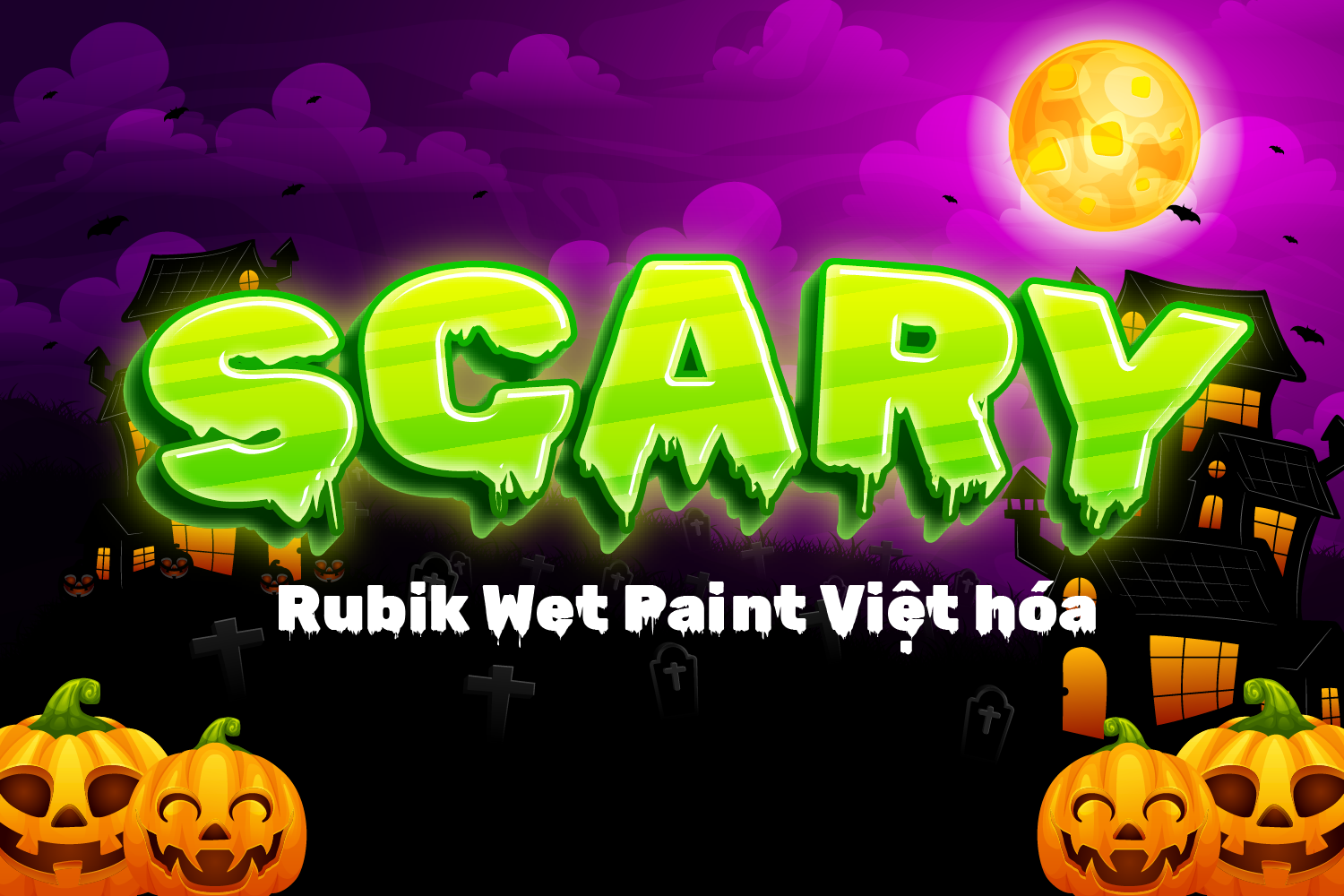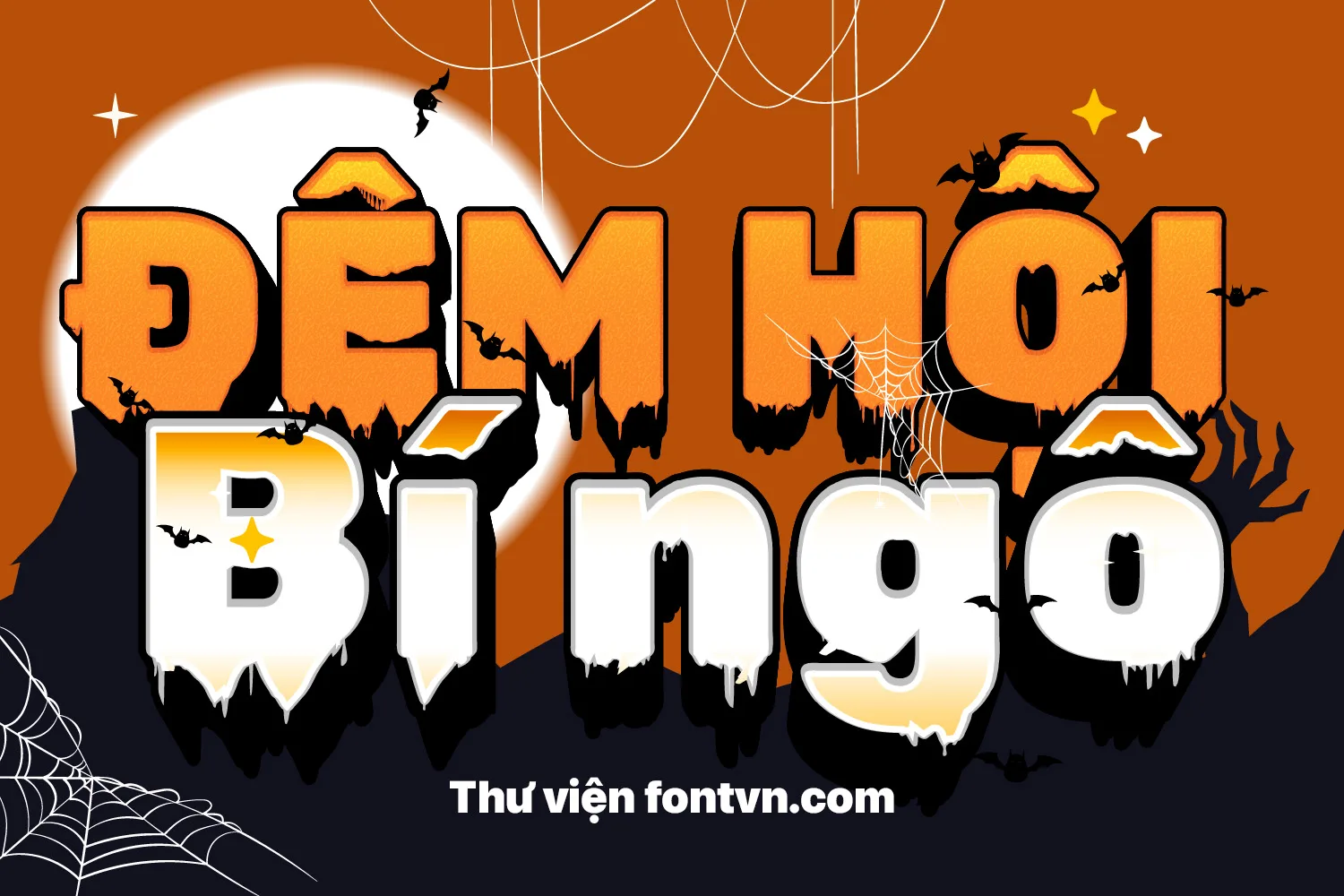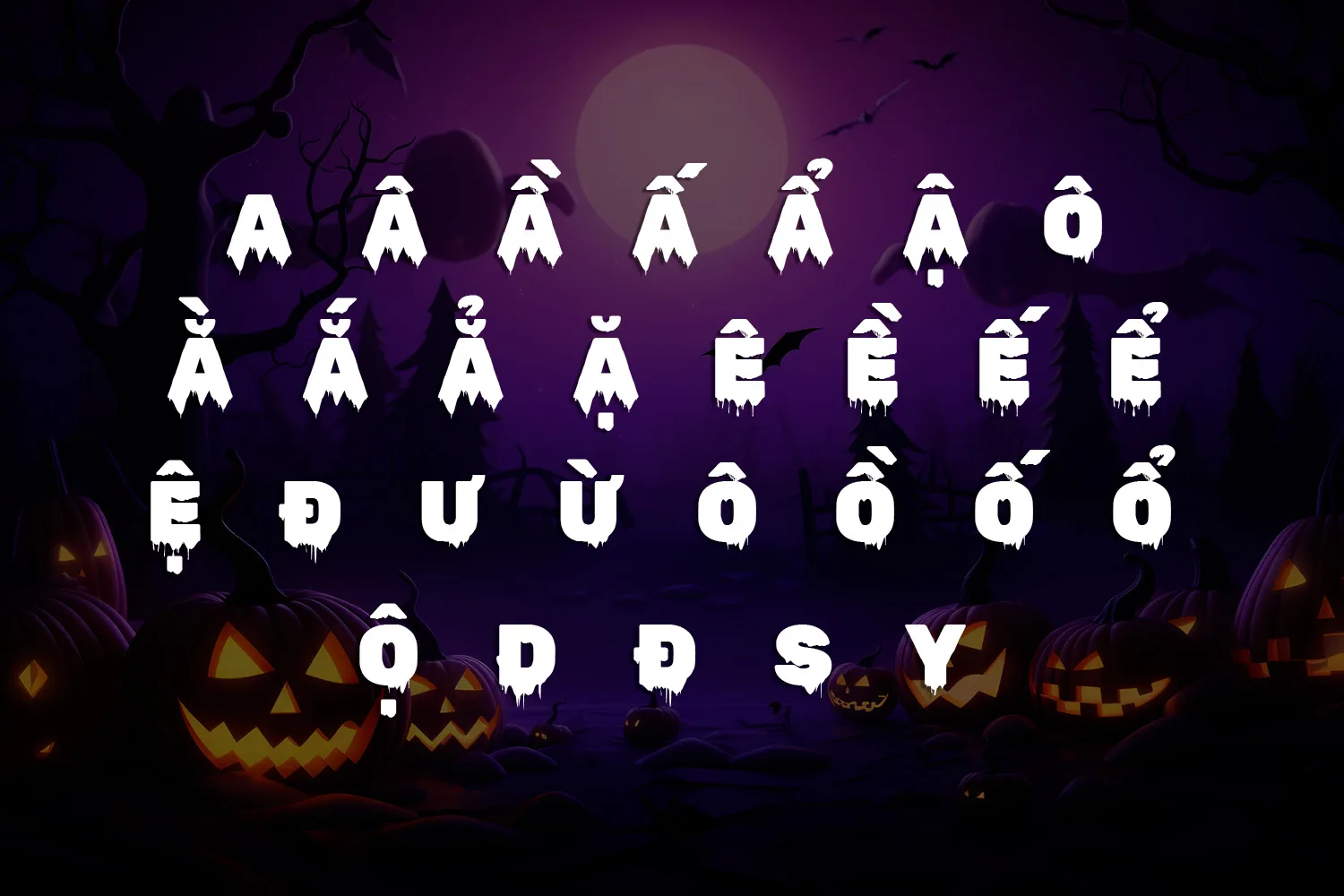
DVN Rubik Wet Paint Việt hóa – Font chữ ma mị cho mùa Halloween
Rubik Wet Paint là một kiểu chữ độc đáo mang phong cách ma mị – rùng rợn rất phù hợp cho các thiết kế Halloween, poster phim kinh dị hoặc các dự án sáng tạo mang chủ đề u ám, huyền bí. Font mang đặc trưng là các nét chữ đậm, chảy nhểu như sơn ướt tạo cảm giác ghê rợn nhưng vẫn dễ đọc.
Ứng dụng của font chữ rất đa dạng
• Thiết kế poster Halloween, banner sự kiện, thiệp mời, standee trang trí.
• Tiêu đề game, video hoặc phim hoạt hình kinh dị – hài hước.
• Các dự án sáng tạo theo phong cách spooky, horror hoặc playful.